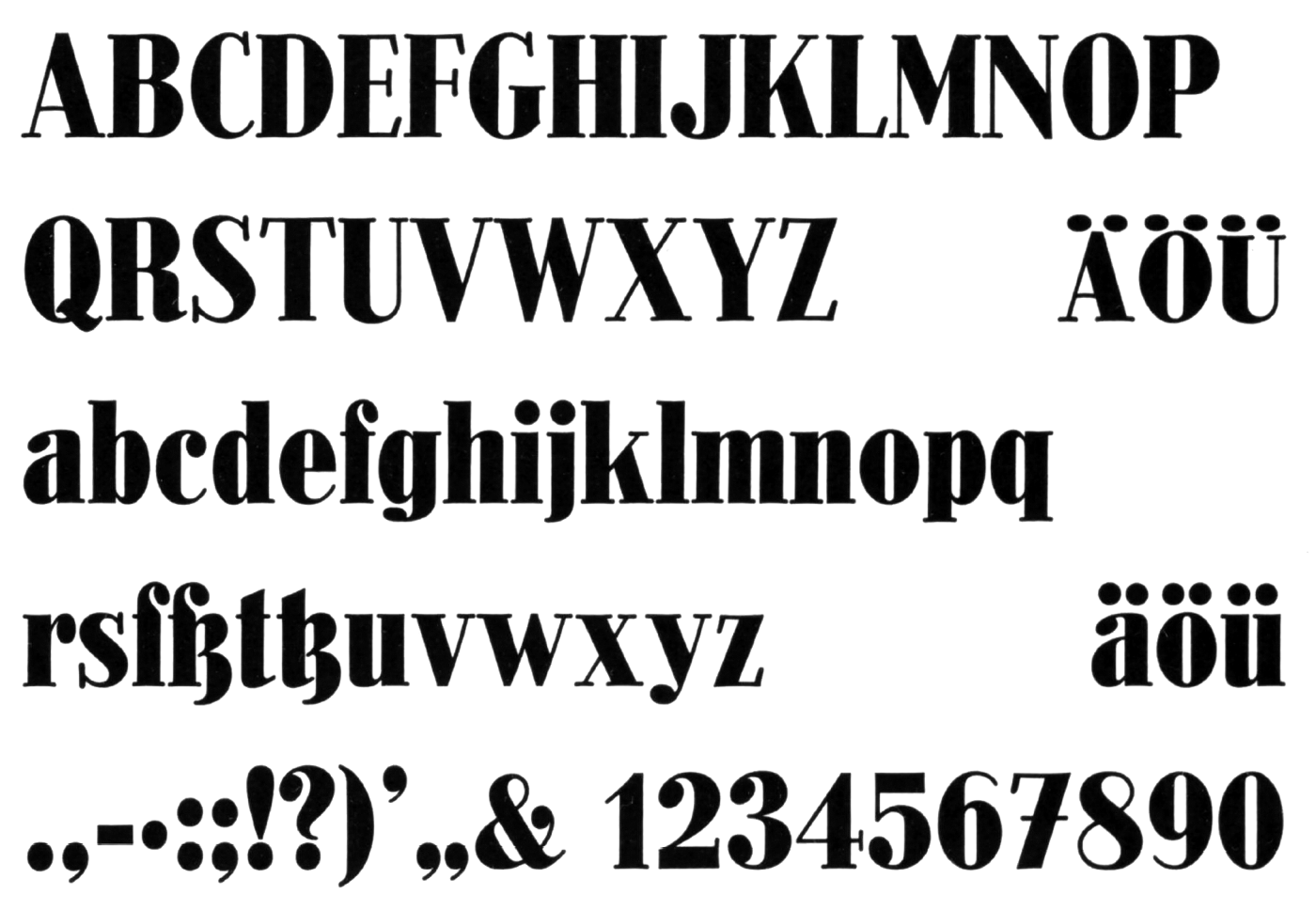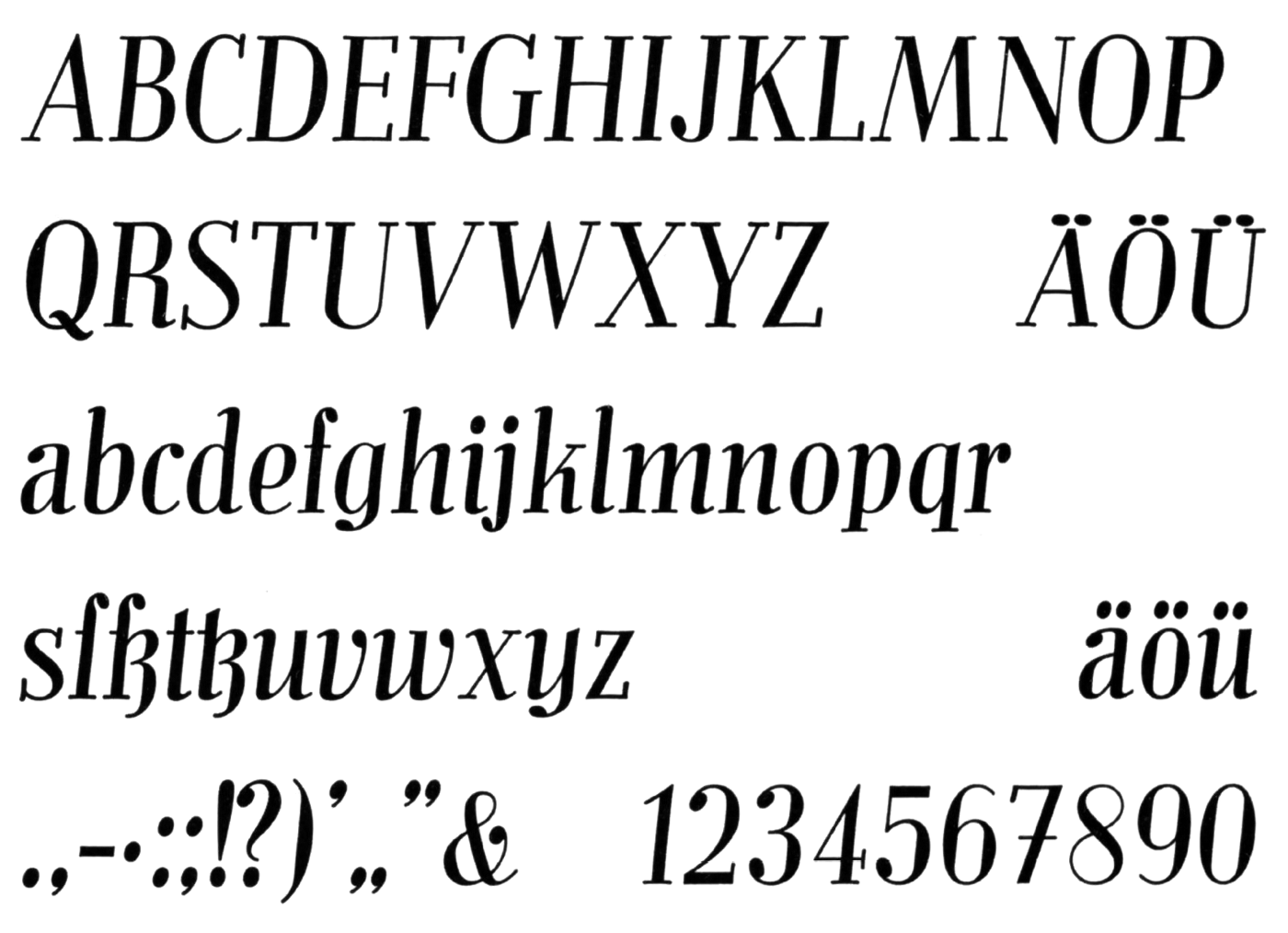
Font-Wiki: Die Schlanke
Die Schlanke ist eine schmallaufende statische Antiqua-Schrift von Walter Höhnisch und erschien Ende der 1930er-Jahre bei der Gießerei Ludwig & Mayer. Die Familie verfügte über die Schnitte mager, kursiv, halbfett und fett.
Digitalisierungen sind nicht bekannt.